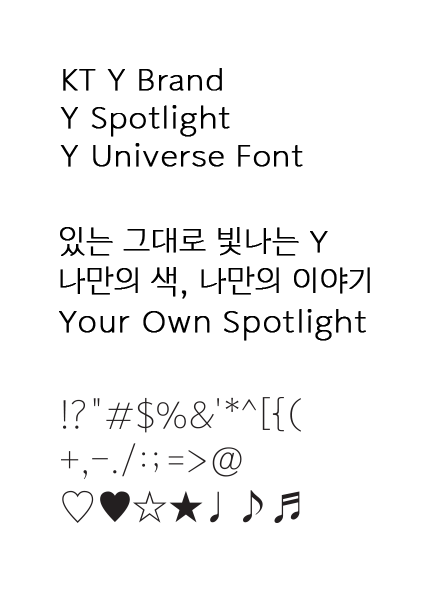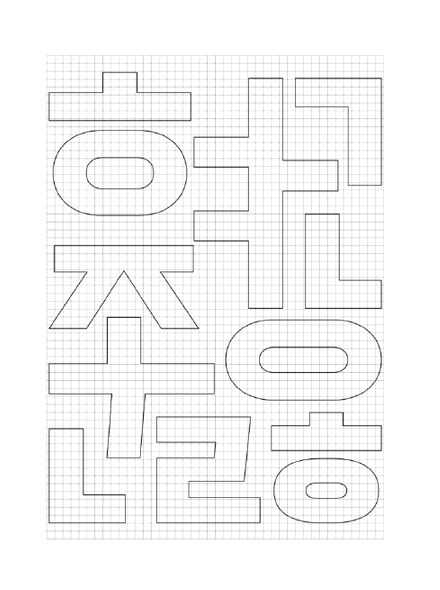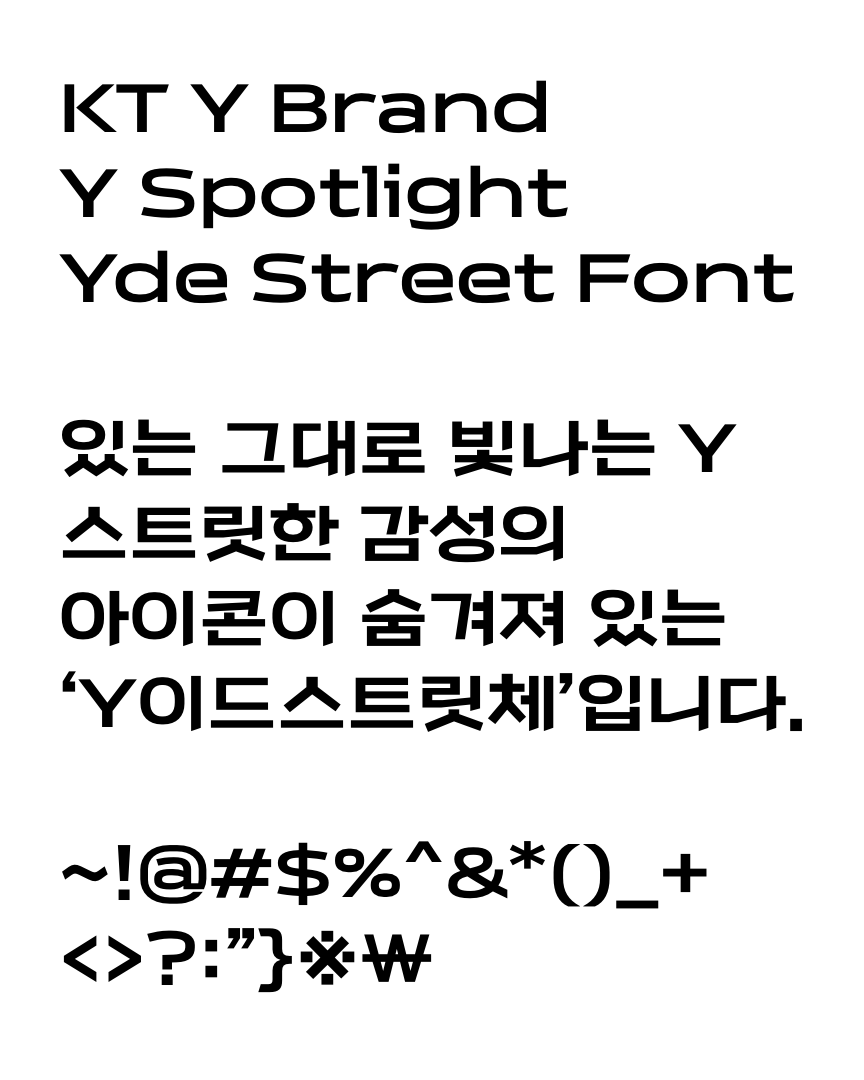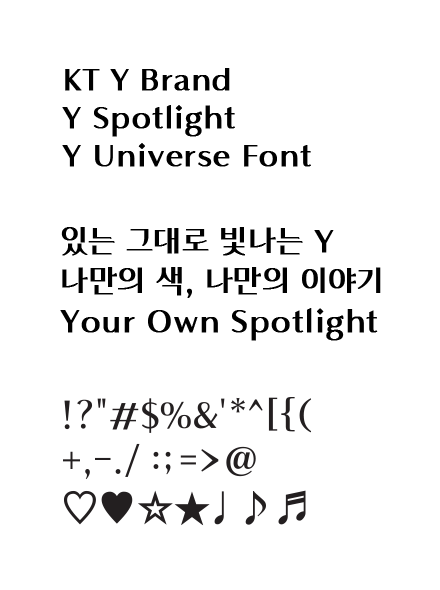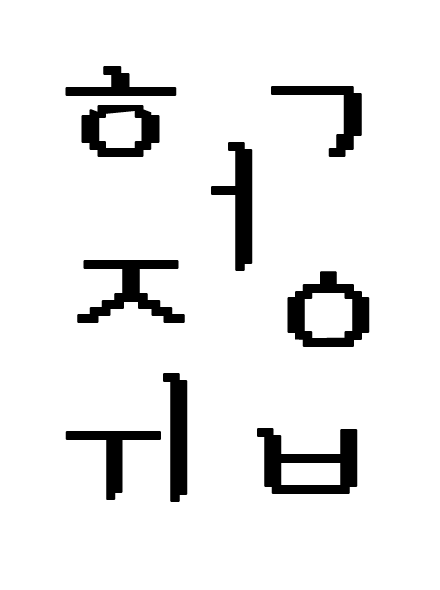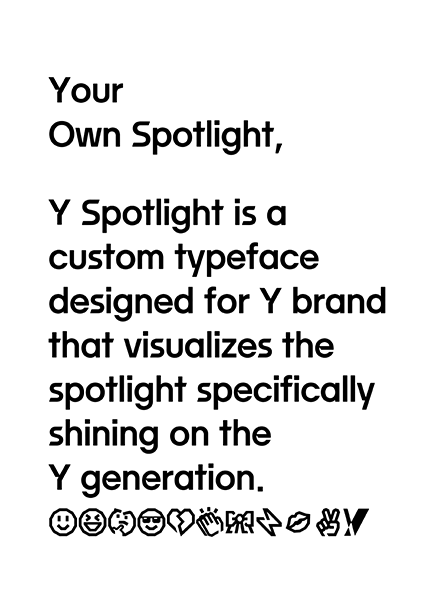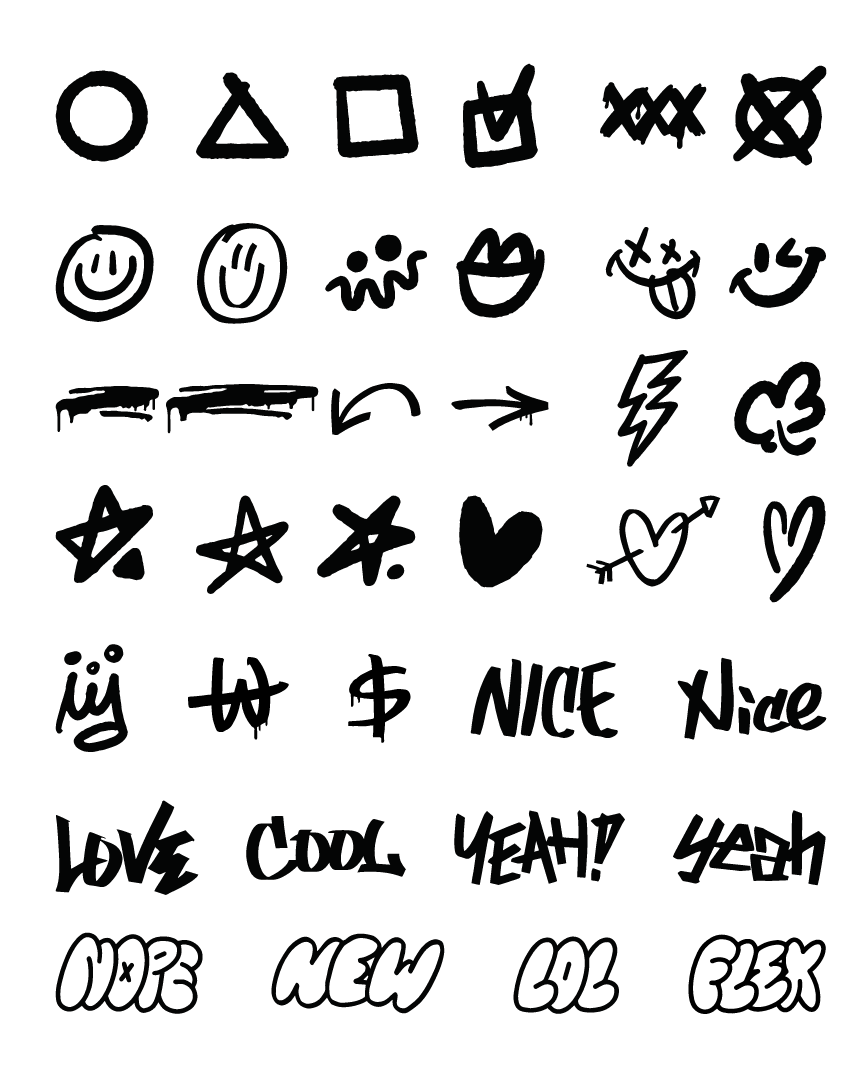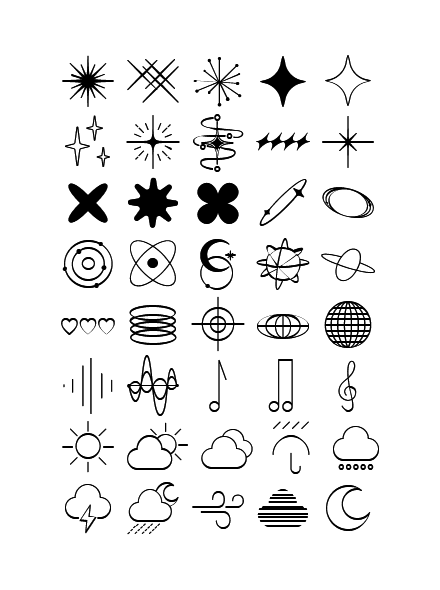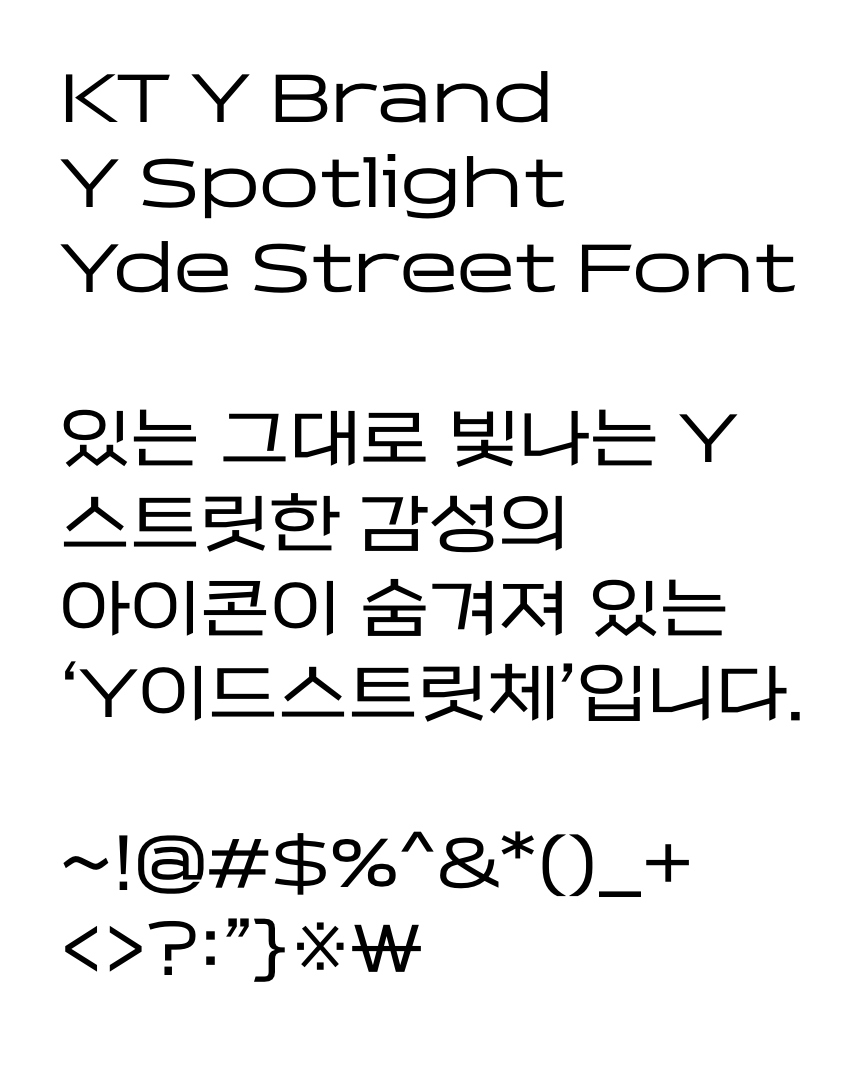
Y의 개성을 담아 스트릿한 감성의 아이콘이 숨겨져 있는 Y의 와이드 서체입니다. Y BRAND FONT
Y개성을 담아 와이드하고
스트릿한 감성의 이모지 37종
Y세대만을 위한
스포트라이트의 형상을
시각화하여 설계된
Y 브랜드만의 서체입니다.
Y BRAND FONT
나를 위한 이모지 33종
'와''이'와 연계된 한글 낱자 중 자주 표현하지 않는 낱자에 이모지 33종 매치
온유한 곡선이 강조된 부드럽고 따뜻한 감성의 서체로 유니버스를 표현한 아이콘들이 숨겨져 있어요~! Y BRAND FONT
자신만의 색으로 빛나는 Y의 유니버스를 기하학적 그래픽으로 표현한 아이콘 40종
디지털 환경에서 나고 자란 Y의 디지털 네이티브 아이덴티티를 담은 비트맵 서체입니다. Y BRAND FONT
옛날 콤퓨타의 추억을 불러일으키는
레트로 비트맵 스타일 아이콘 44종